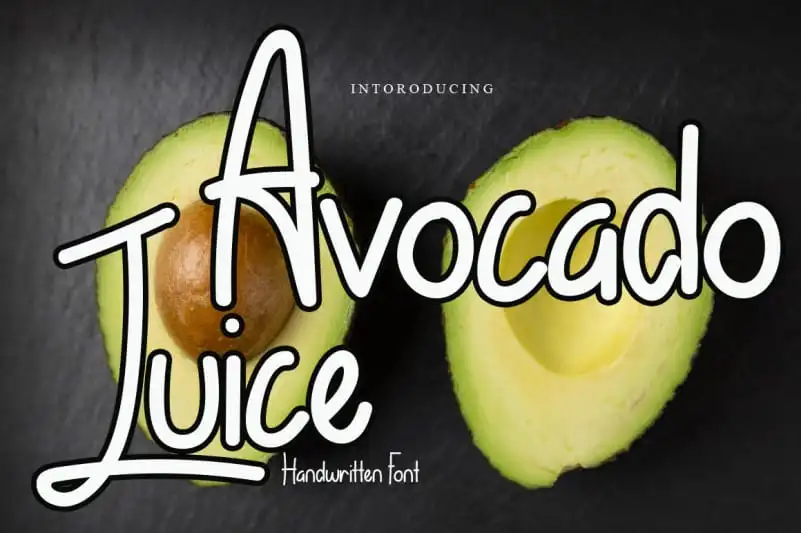
Avocado Juice Display Font – Download Grátis
A Avocado Juice Display Font é uma fonte à mão escrita relaxada e fresca. Suas características naturais e únicas a tornam perfeitamente adaptável para uma ampla gama de projetos. Ela traz um toque leve e descontraído, ideal para criar designs vibrantes e divertidos. Independentemente da ideia criativa que você tenha em mente, essa fonte será o recurso visual perfeito para dar vida a seu design. Seja você um designer gráfico jovial ou alguém que busca uma maneira única de expressar sua personalidade através dos materiais digitais, Avocado Juice Display Font está aqui para ajudá-lo.